虽然有成千上万的免费字体可供在线下载,但有时很难遍及所有可用字体。
我们汇总了15种出色的手写字体列表-字母,毛笔和书法字体-这些字体大多数都可以下载而没有附加任何字符串,可以用于商业目的。在某些情况下,您可能必须共享您的电子邮件地址才能下载字体。
1。 Cavorting
Cavorting是一种很棒的手写笔刷字体,可免费用于个人和商业用途。如果要使用Photoshop在下面的屏幕截图中获得相同的效果,请查看本教程。此技巧将与列表中的许多字体派上用场。
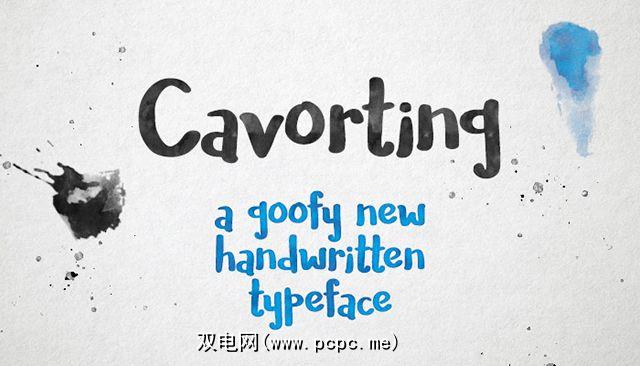
2。 Mathlete
Mathlete有四种样式,也可以用于个人和商业工作。字体只能以大写字母显示。如下例所示,这是地址标签的绝佳选择,因为它具有手写体但清晰易读,并且包含大量字形。
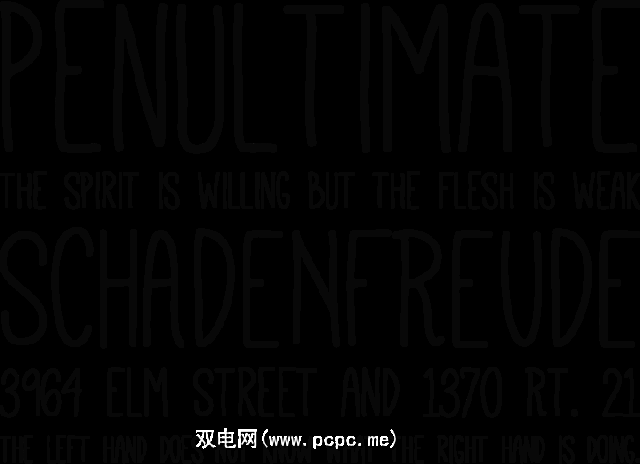
3。 Sunn
Sunn与Mathlete相似,不同之处在于外观更为简洁。要下载Sunn,您必须提供您的电子邮件地址。字体的扩展版本仅售4.95美元,并带有其他字体和西里尔字母。
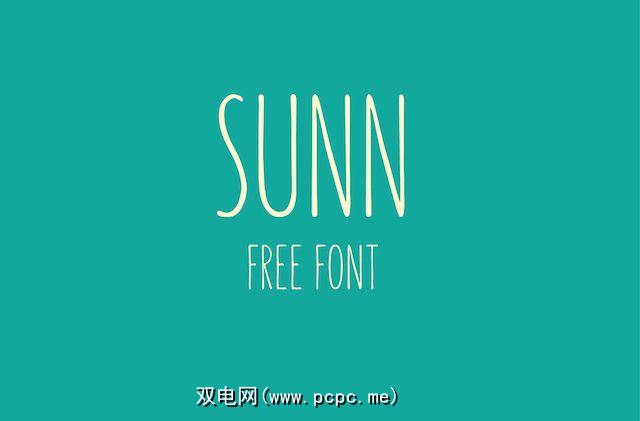
4。 Mighty Type
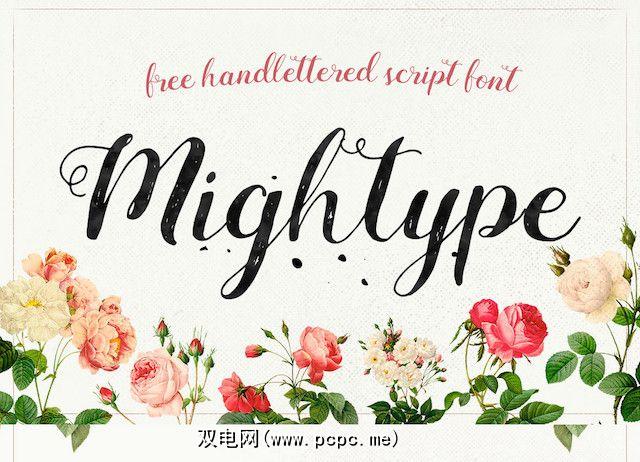
5。 Barokah
Barokah是常规字体和粗体字体,可用于个人和商业项目。该字体将适合漫画设计。
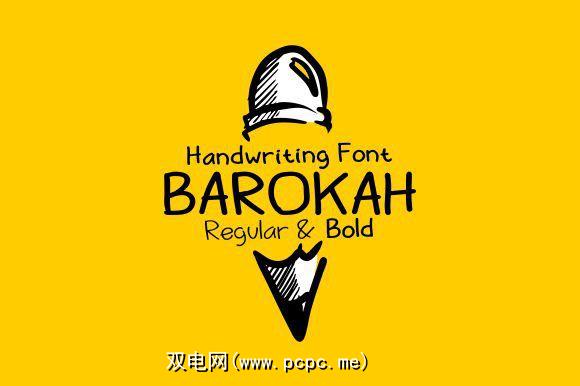
6。 Arabella
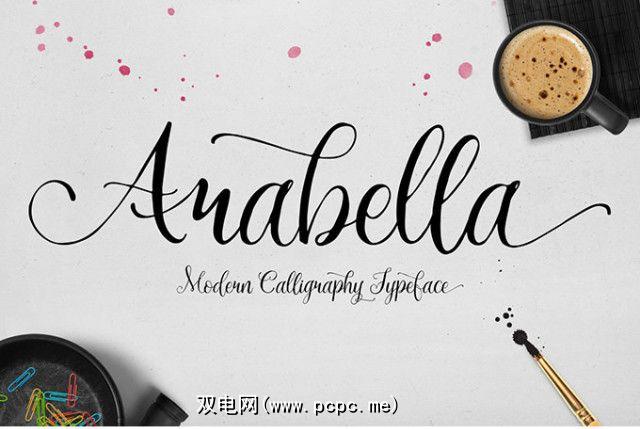
7。 Cutepunk
Cutepunk具有很好的复古感,您可以免费下载没有附加任何字符串的字体。它带有三种字体(常规,浅色和粗体),并且该字体可用于个人或商业用途。
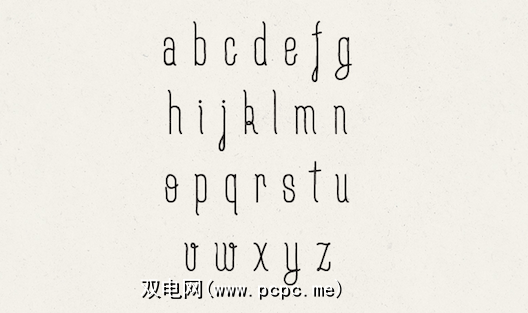
8。 Skinny
如果您想要Cutepunk之类的东西,但手写笔或孩子般的外观更真实,请尝试一下Skinny。字体只能使用大写字母。
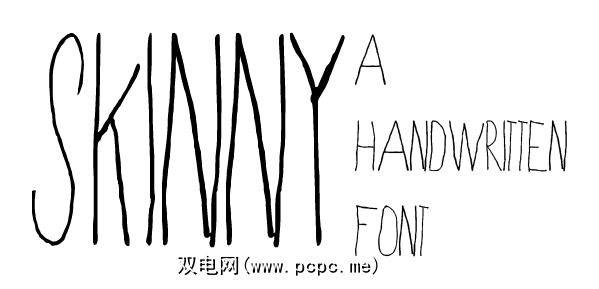
9。 Waterlily
Waterlily是另一种有吸引力的免费画笔字体,效果很好,与上面链接的教程有关如何使您的字体看起来像是用Photoshop水彩画的教程一样。包含所有字形的字体可用于个人或商业用途。
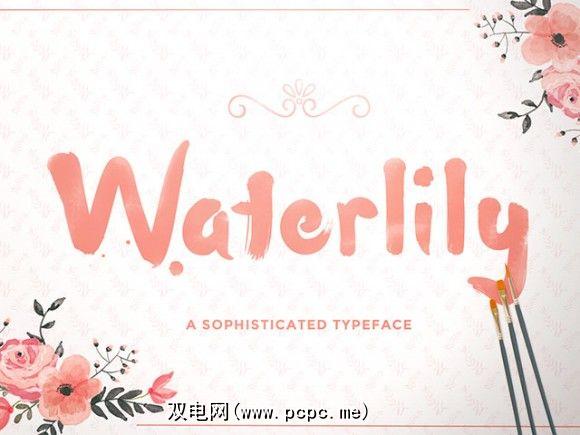
10。 Mf I Love Glitter
此草书字体仅供个人使用,但具有可爱的小功能,这在免费字体中很少见。使用括号,下划线,星号和竖线,您可以在文本上添加小小的心形和漩涡形。在此处了解有关如何执行此操作的更多信息。
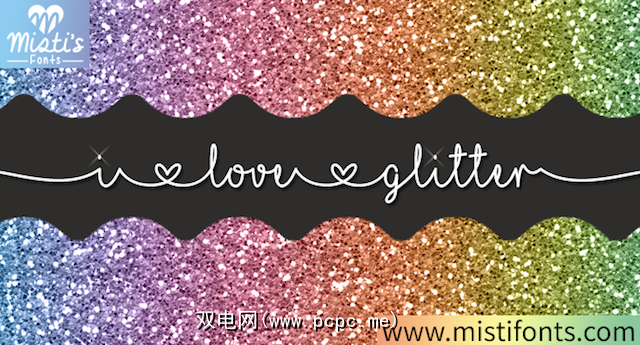
11。 Sophia
该书法字体可免费用于个人和商业用途,它还具有有趣的功能。您还可以使用两个额外的字体在每个单词或句子的开头和结尾添加漩涡。
12。 BlowBrush
BlowBrush是另一种出色的毛笔手写字体,但实际上与其他字体(通常是涡旋的书法字体)区分开来。该字体可免费用于个人或商业用途。
13。 Skraw [不再可用]
对于适合儿童设计或剪贴簿的草或sc草外观,Skrawk可用于个人或商业用途。
14 。 Tragic Marker [不再可用]
Tragic Marker是一个很好的选择,如果您正在寻找看起来像是使用标记写的手写字体。该字体可用于个人或商业用途。在Photoshop上使用笔刷之类的标记,您也可以使用本文前面列出的教程在文本中添加该标记感。
15。 Banthers
Banthers免费提供商业和个人使用,是复古或垃圾外观的绝佳选择。